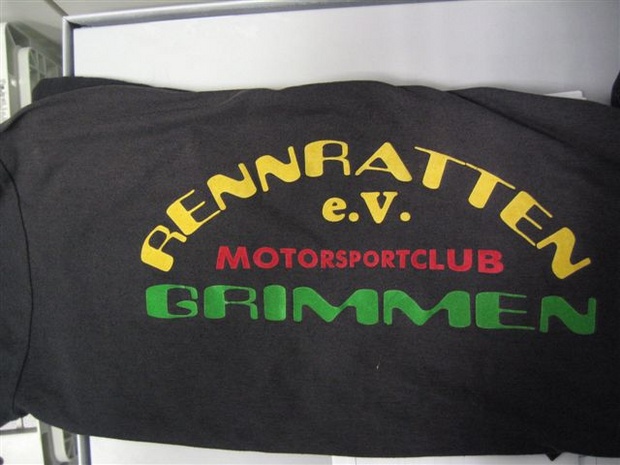
ich bin neu hier und bitte euch um Hilfe, da ich leider einfach nícht weiter komme. Ich habe eine Schrift auf einem Shirt und diese soll wieder auf ein neues Shirt. Leider kann ich nicht in Erfahrung bringen wer die Sachen gemacht hat, noch wie dieser Font heißt. Daher meine bitte um Hilfe, sonst muß ich weiterhin die Fontseiten Quälen ;o)
Ist ähnlich der Amelia, aber so richtig kommts nicht hin.
Amelia passt schon. Einfach auf ein Drittel der Höhe quetschen …